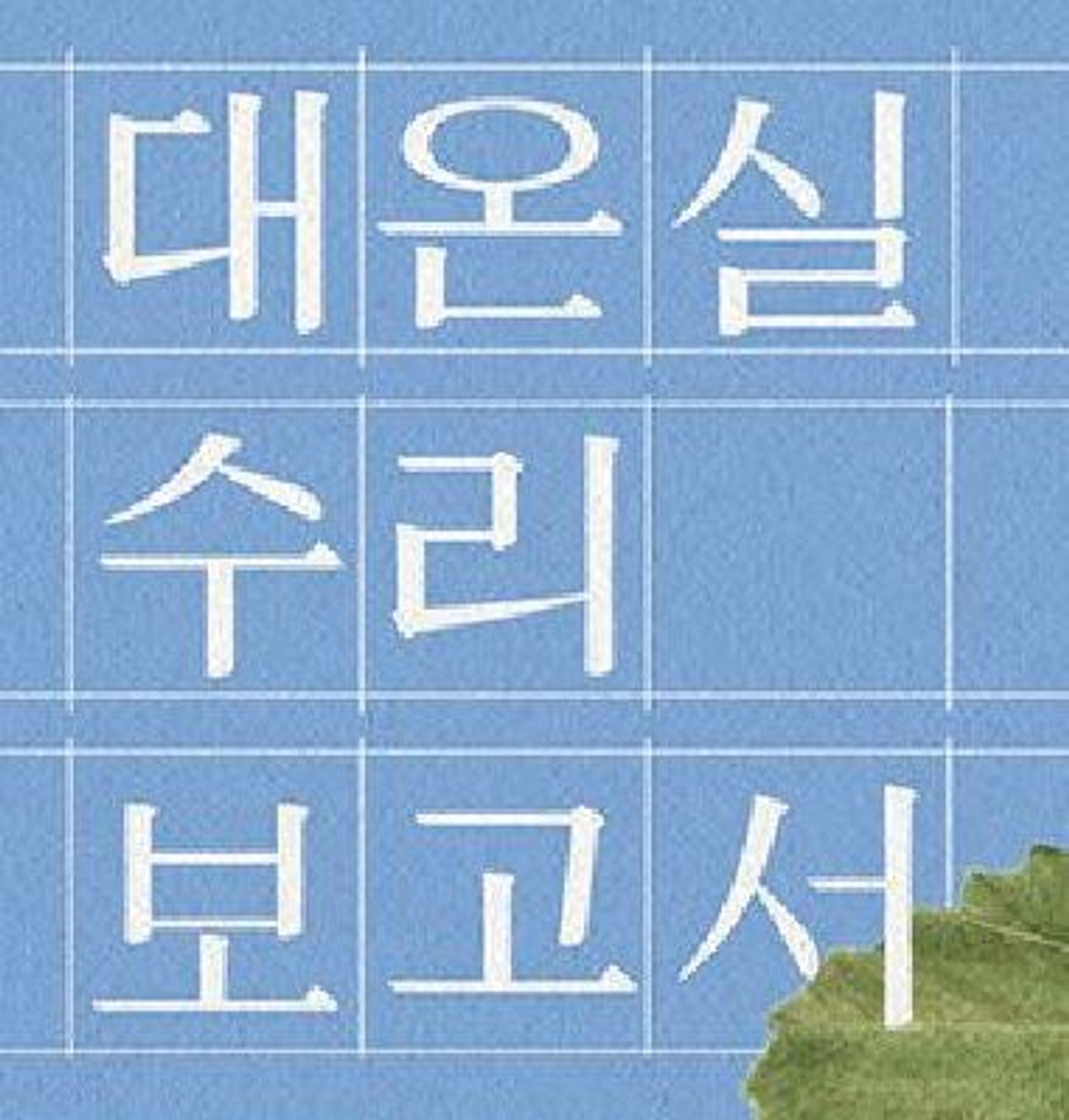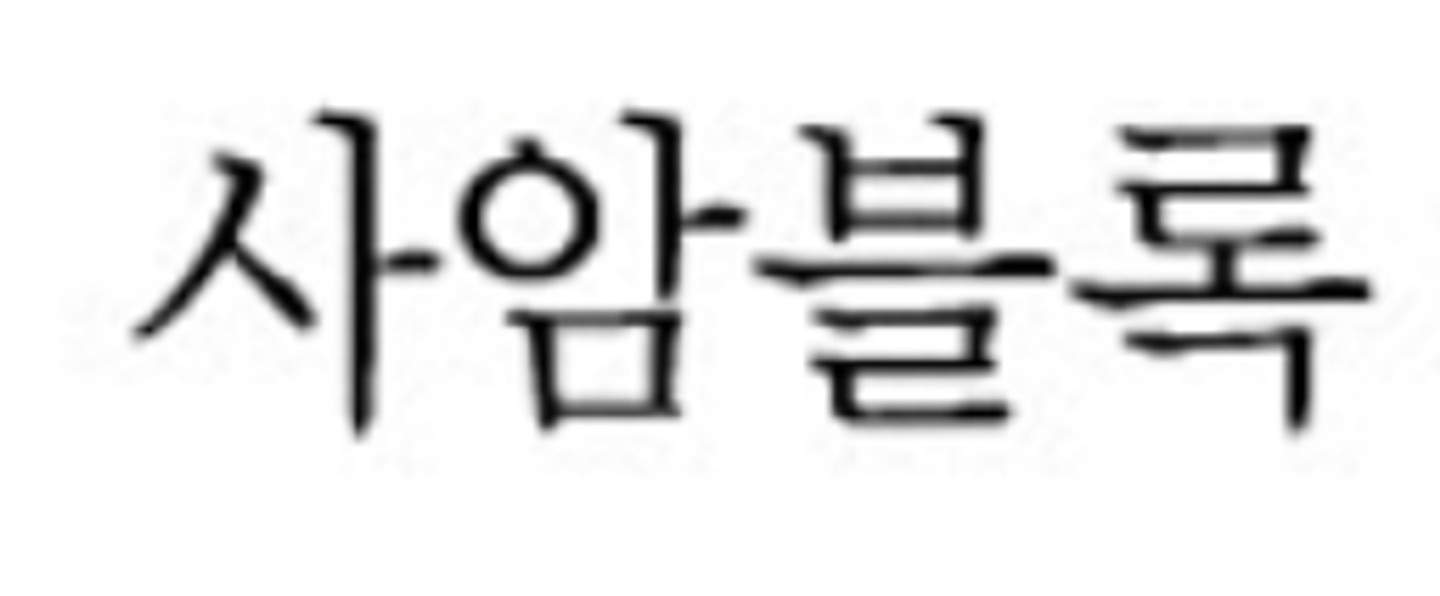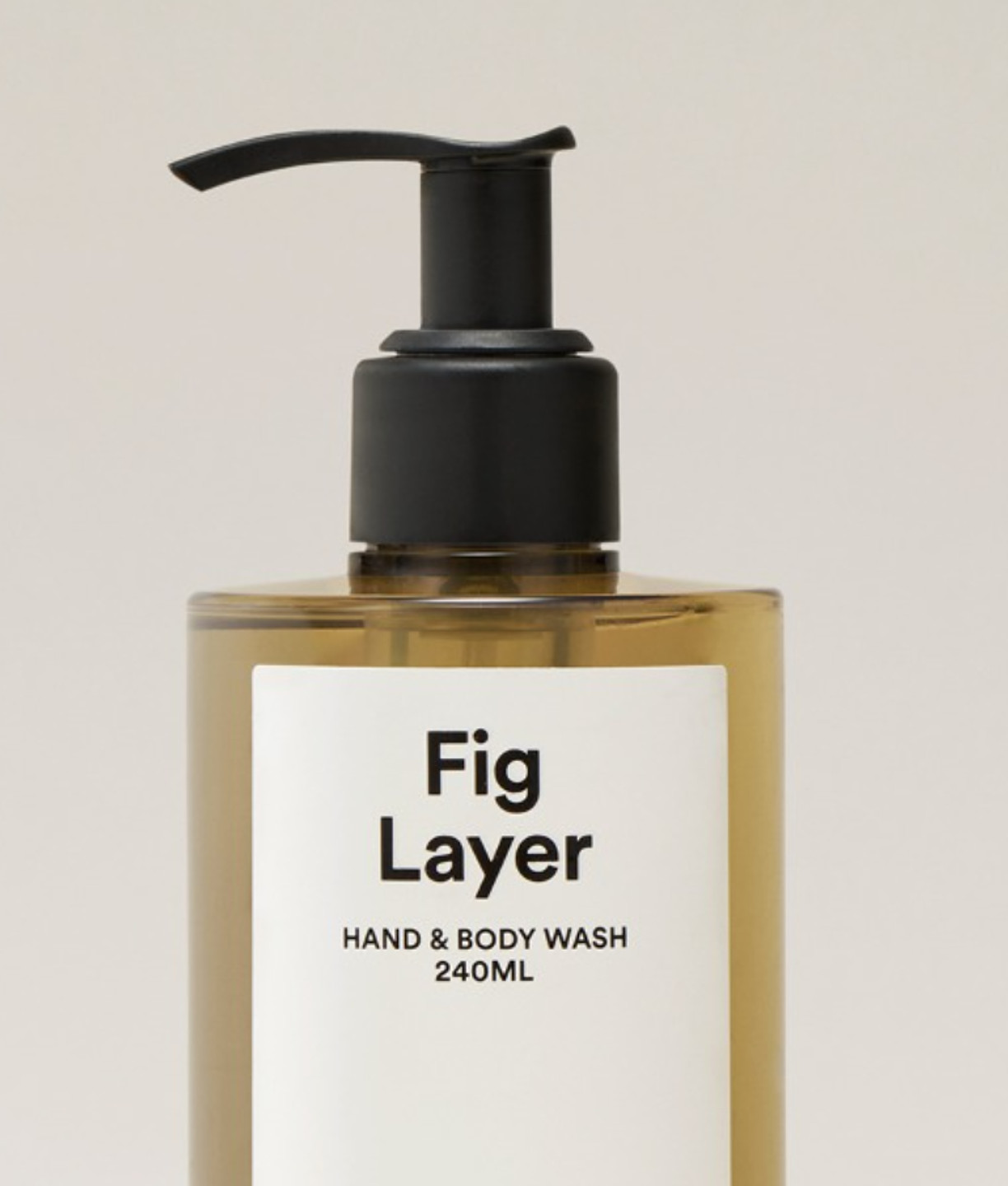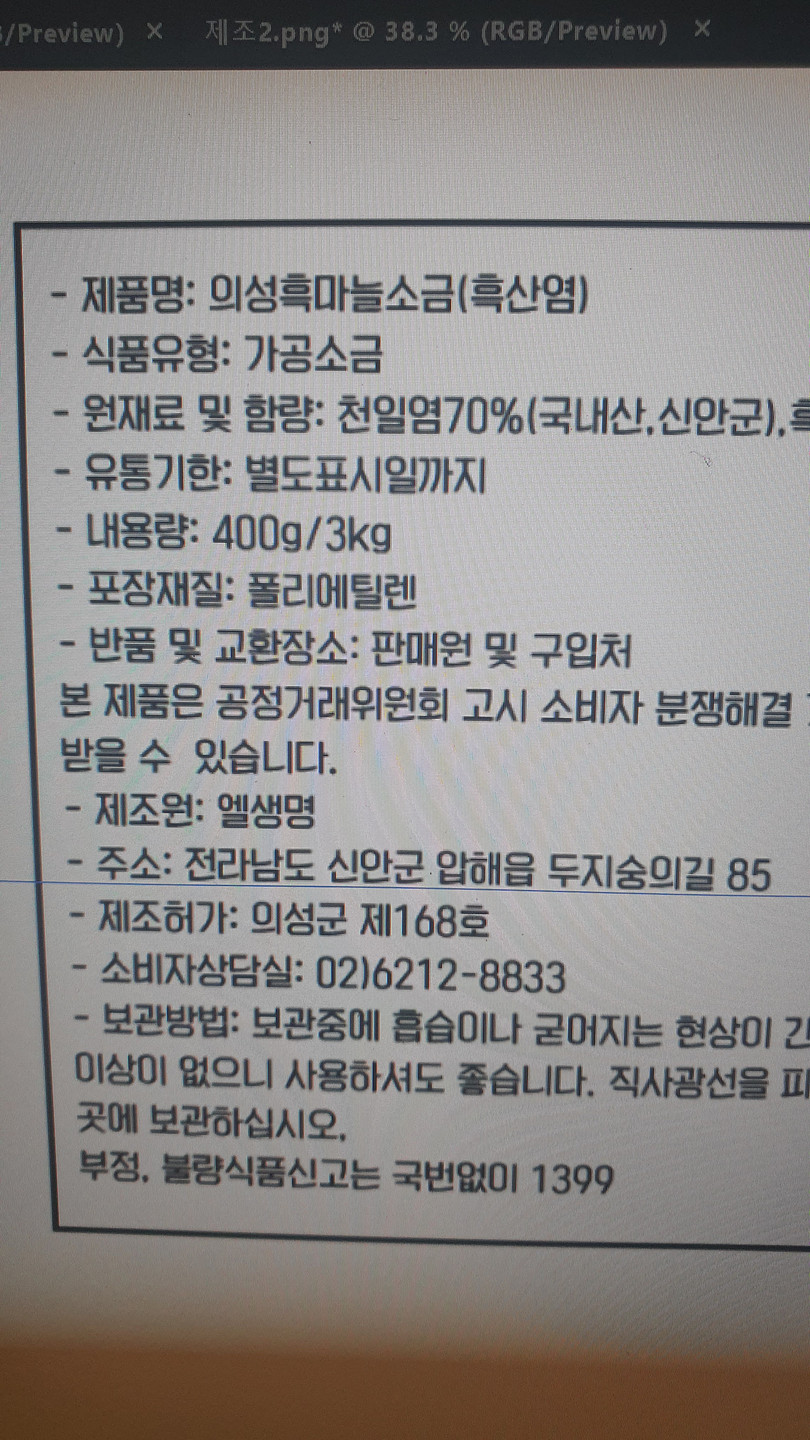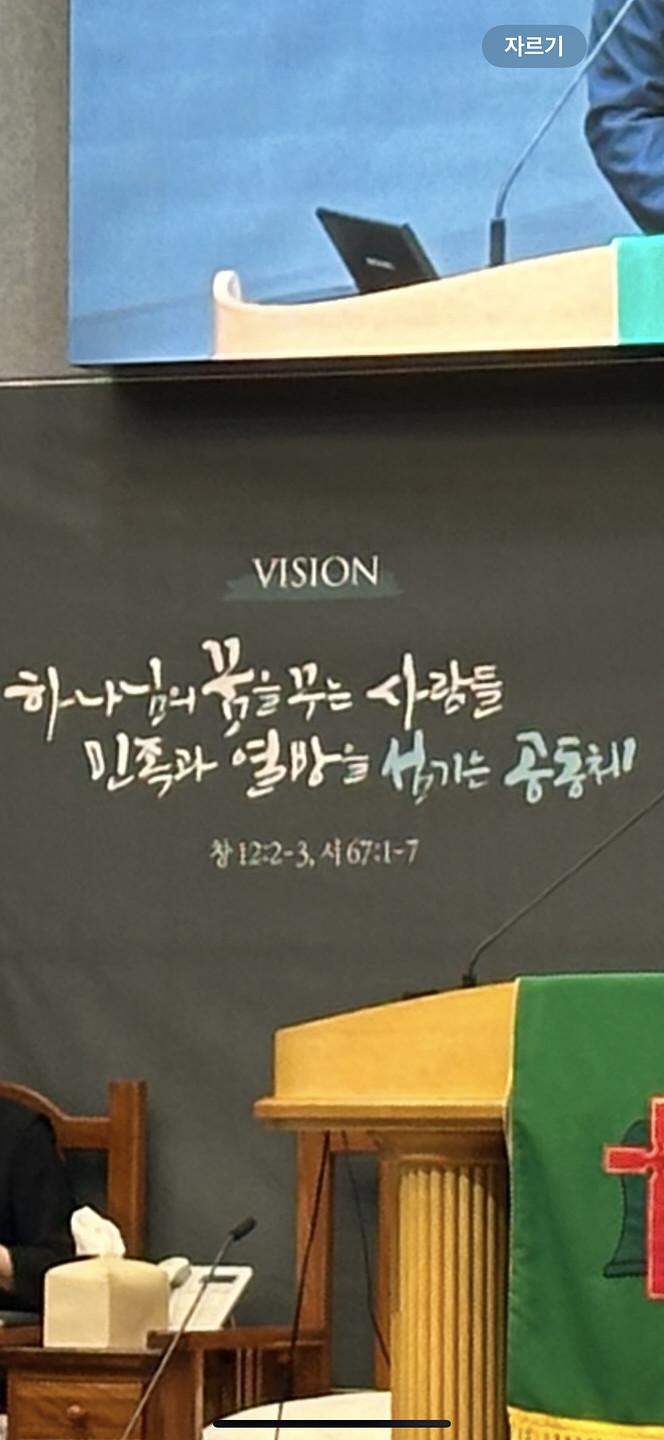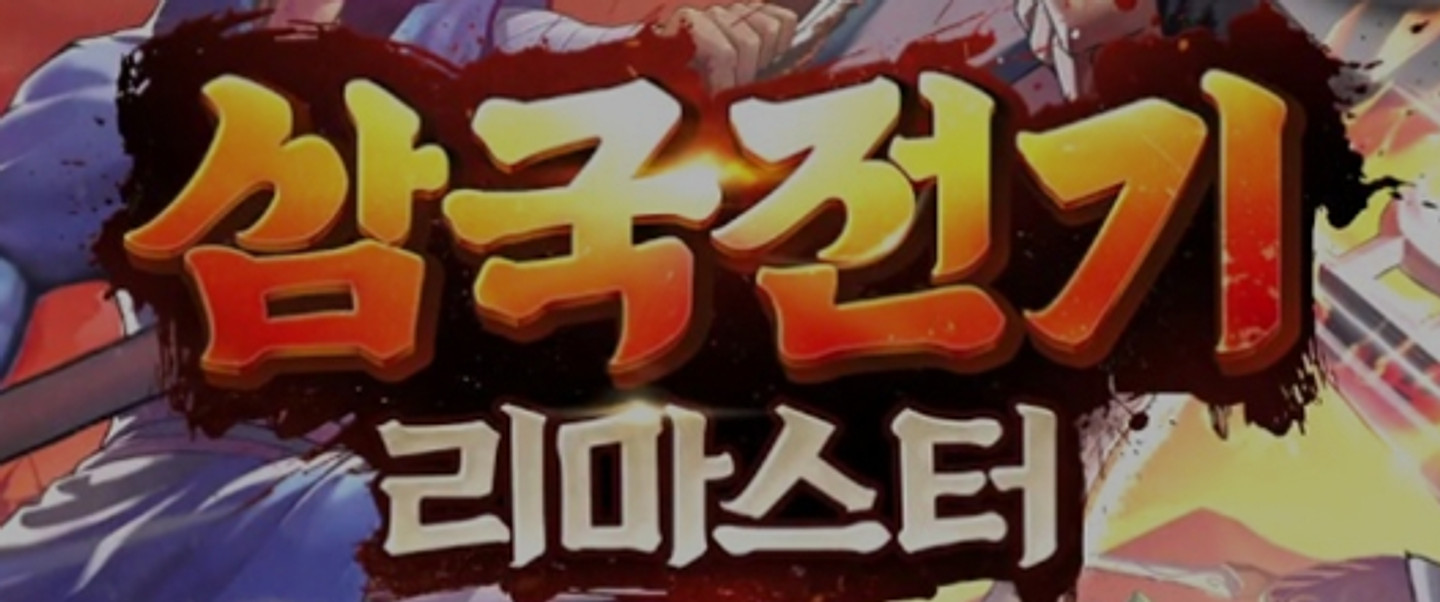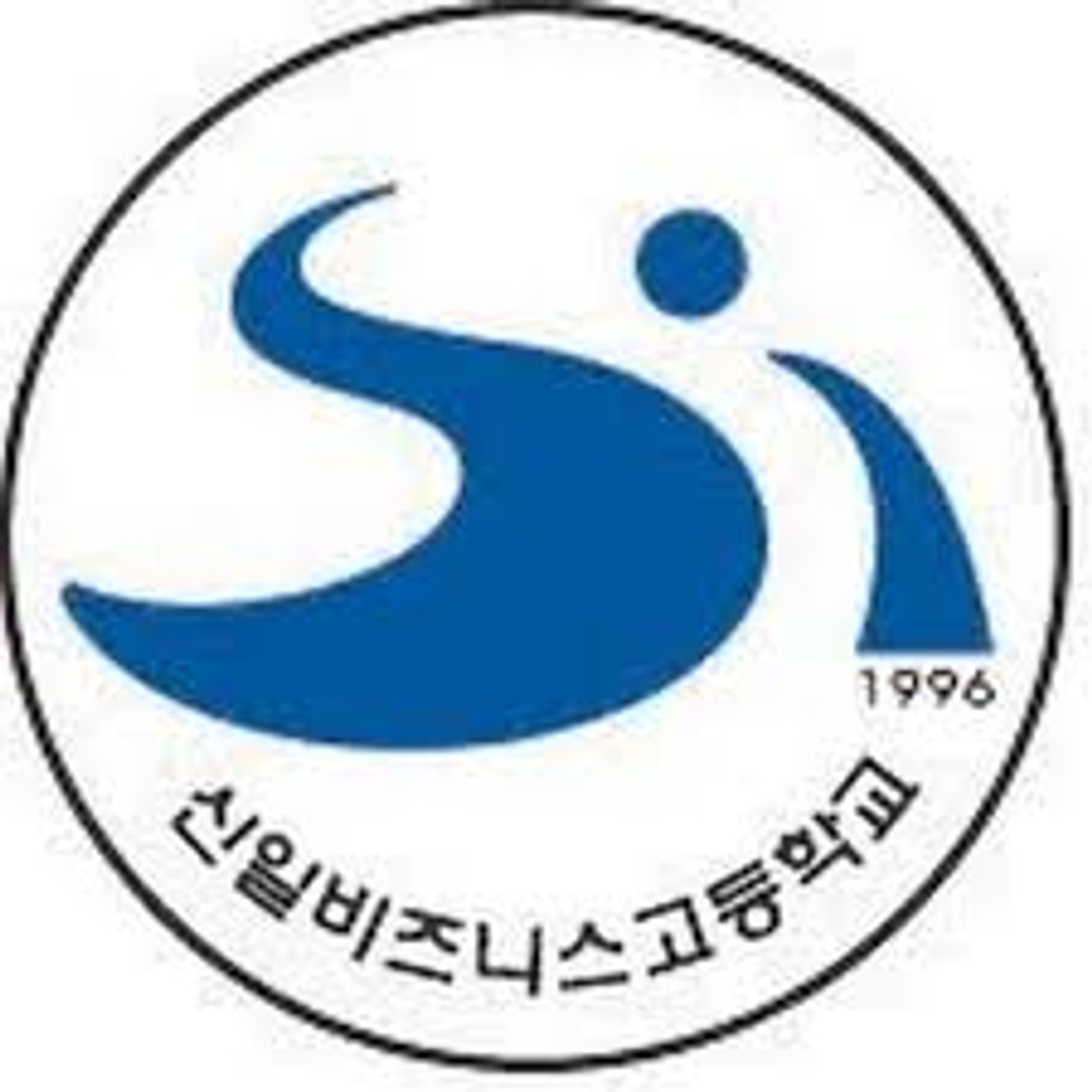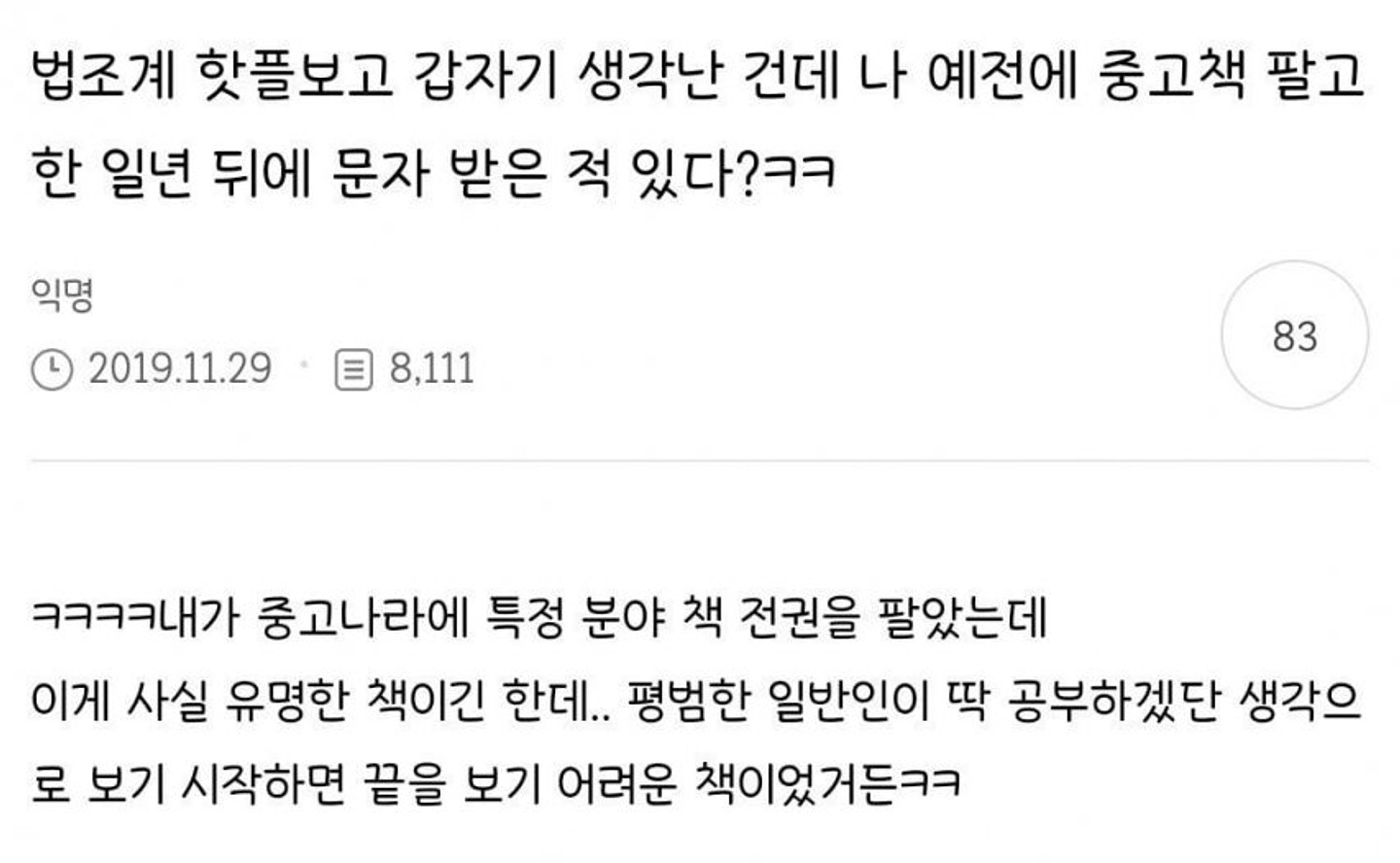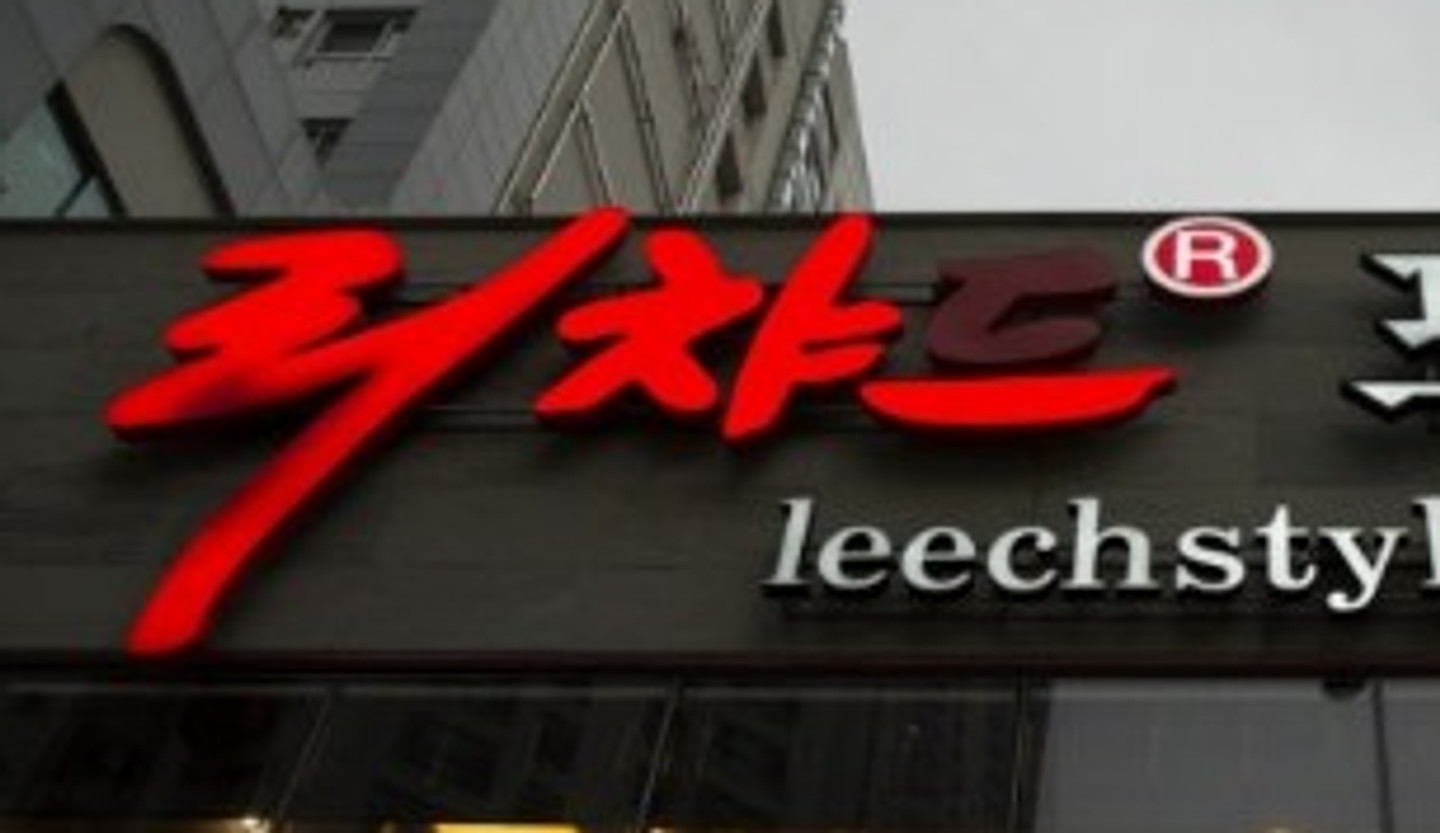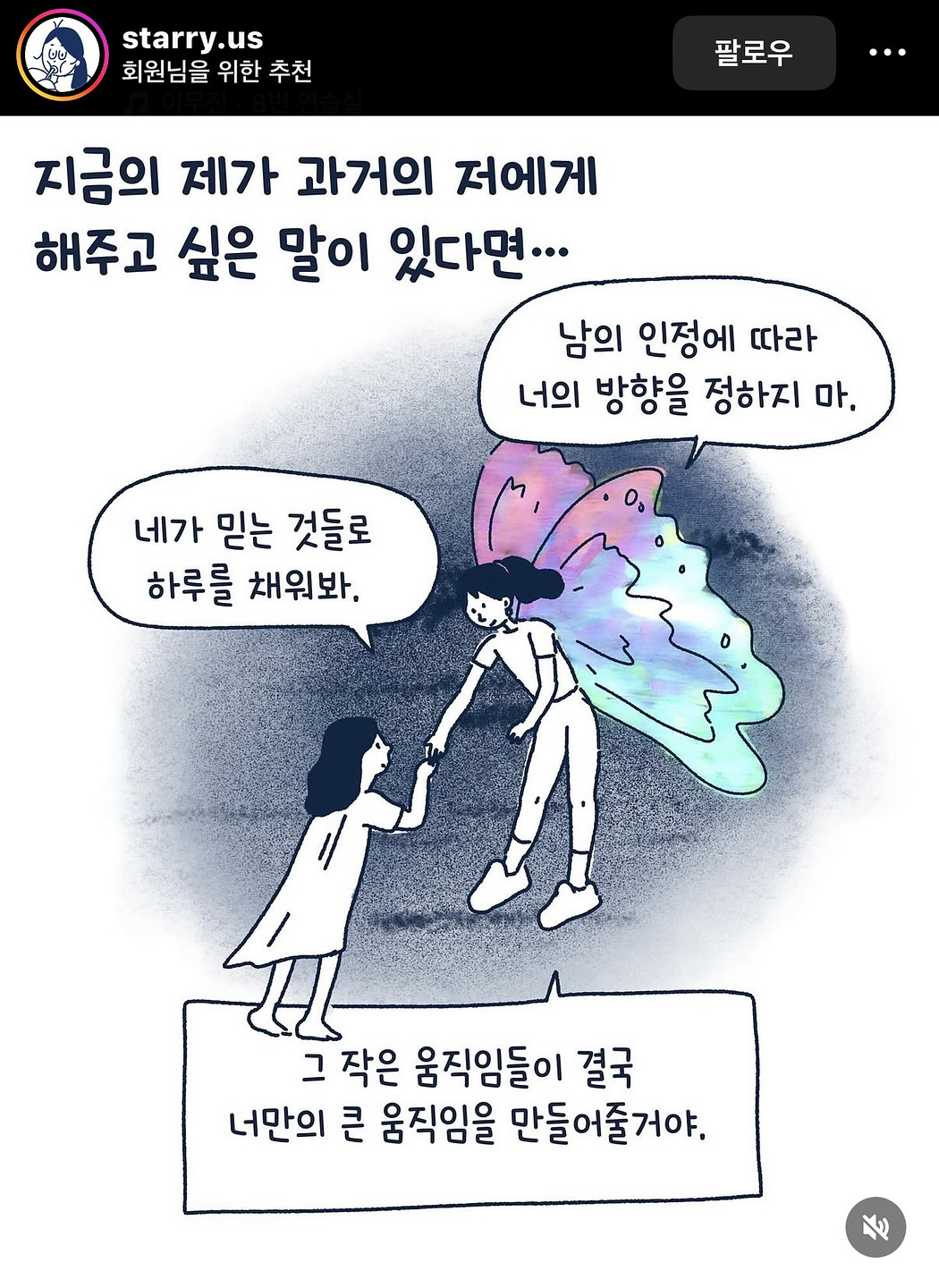
콜미베이비에 나온 폰트인데 어떤 폰트인지 궁금합니다!!
폰트 마스터들이 있다고해서 찾아왔습니다!!! 26 기아타이거즈 마킹 글씨체에요! 이름이랑 숫자가 다른 글씨체 같은데..ㅠㅠ 뭔지 모르겠어요ㅠㅠ 찾아주실 분 있나요!
이 폰트좀 찾아주세요ㅜㅜ
대표메뉴와 아래 국내산 서체이름이 뭘까요... 똑같은 서체를 써야한다고 하셔서 꼭 찾아야 합니다..ㅠㅠ 도와주세요..ㅠㅠ
'요맘때패스'에 쓰인 폰트를 자주 보는데 요게 어떤 폰트인지 궁금합니다.. 이런 올록볼록 두툼한 폰트를 찾고 있어서요 ㅠㅠ
이 글씨체 너무 알고싶어용!!
무슨 글씨체일까요···
이 폰트 어떤 폰트일까요?
무슨폰트인지 궁금해요!!
이거 타이틀 폰트 어떤건지 알수 있을까요?
이 폰트가 뭘까요?
폰트 정보 궁금해요
무슨 폰트인지 아시는분 숫자가 되게 특이해요 ㅠ
폰트 고수님 알려주세요~~
폰트를 찾습니다
해당 폰트를 찾습니다. 어떤것인지 모르겠네요..
무슨 폰트인가요¿
폰트 이름이 뭘까요?
이 글씨체 알려주세요ㅜㅜ
이거 뮤슨 폰트인가영 ㅠㅠ
이 폰트 뭔지 아시는 분..!!
무슨 폰트일까요?^_^
이 폰트가 궁금해여 아무리 찾아도 안나오네여
이 릴스에자주보이는 각진?폰트 이름이 뭘까요ㅜㅜ
이거 글씨체 뭔지 궁금해요!! 글자 위에 하트 들어가는 게 어떤 폰트인지 모르겠어요ㅠㅠ
저 장식체는 로고 디자인일까요? 아니면 폰트일까요? 폰트 아시는 분 있으시면 알려주시길 간절히 빕니다ㅠㅠ
이응이 사과머리 묶고있는 이 귀여운 폰트 꼭 알려주세요
폰트 이름 궁금해요,,
이런 거 폰트가 잇나요?? 아니면 걍 효과인가여? 원래 폰트가ㅜ멀까여 ㅠㅠ
이 폰트 뭔가요? 기다리겠습니다
이 폰트 제발 알려주세요 ㅜ
이 피피티에 폰트좀 알려주세요 ㅠㅠㅠㅠ
이거 무슨폰트졍?
과제하고 있어서 폰트 변경해야 하는데 혹시 이거 무슨 폰트인지 알려주시면 감사드리겠습니다..!
곤색으로 되어 있는 글씨체 알고 싶어요
이 폰트가 무엇일까요?
무슨 폰트인지 아실까요? 아님 비슷한 폰트라도... 부탁드려요..
예전에 썼던 것 같은데 이름이 기억 안 나요 ㅠㅠ 폰트 이름 좀 알려주세요 !!
폰트 정보 알고싶습니다
이 폰트 알고 싶습니다!!
이게 무슨 폰트 일까요? 제안서에 들어가는 폰트인데 이미지처리 되어 있어서 같은 폰트로 작성할 수가 없어서 난감하네요;;;;
지마켓 광고에 나오는 자막입니다 무슨 폰트 일까요?
이 폰트 이름 아시는분있나요 ㅜㅜㅜ
폰트이름 문의해 봅니다. 아시는분 계실까요?
유튜브에서 본 폰트인데 무슨폰트인가요 ㅠㅠ 프로그램에 있는 폰트일까요..ㅠㅠ
이 폰트 아시는 분 계실까요~?
해당 폰트 이름 궁금합니다.
부평화랑교회 어떤 폰트일까요 ㅠㅠ?
서체 좀 알려주세요 ㅠ
아트팜 이 폰트 정보 좀 찾아주세요
이거 영문으로 써진부분 폰트 뭔지 혹시알 수 있을까요?
이 폰트가 대략 무엇일까요? 엑스랑 케이가 조금 다른거랑 달라서요.
꼬불꼬불 영어랑도 같이 쓸 수 있는!
유튜브에서 발견했는데 무슨 폰트일까요?